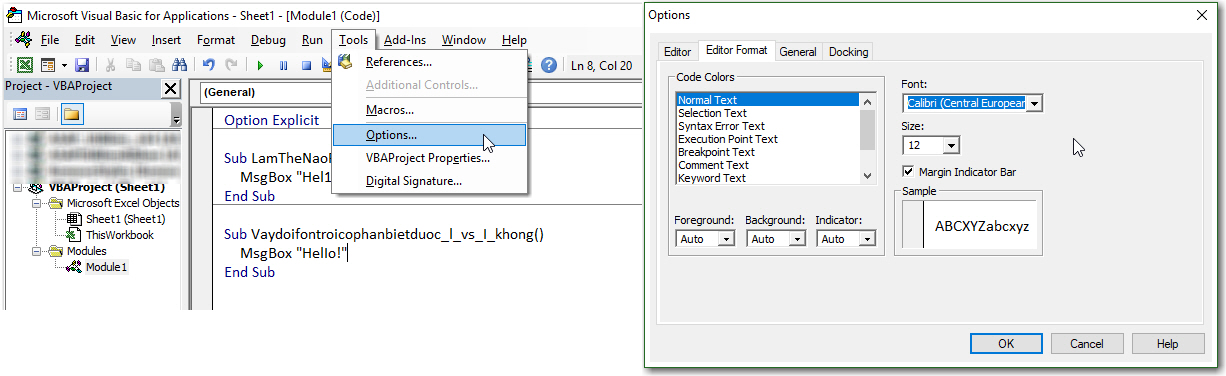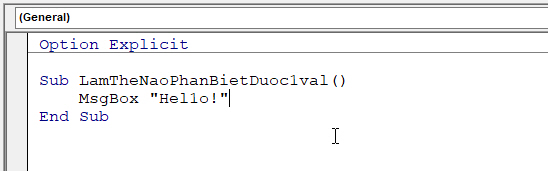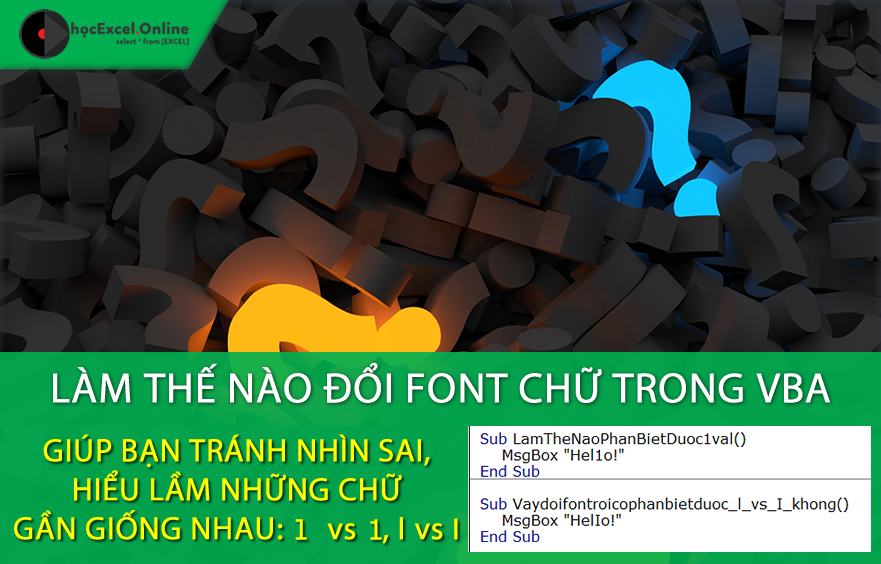
Thay Đổi Font Chữ Trong VBA Editor
VBA mặc định sử dụng font chữ Courier, đôi khi gây khó khăn trong việc phân biệt các ký tự giống nhau như số 1 và chữ l thường.
Thoạt nhìn, chúng trông rất giống nhau. Microsoft đã cung cấp tùy chọn thay đổi font chữ và màu sắc trong VBA editor để khắc phục vấn đề này và giúp bạn lựa chọn font chữ yêu thích.
Để thay đổi, bạn vào Tools -> Options -> Editor Format. Trong phần Normal Text, bạn có thể chọn font chữ mong muốn. Ví dụ, chúng ta chọn font Calibri.
Tuy nhiên, với Calibri, chữ l thường lại dễ nhầm lẫn với chữ I hoa. Mặc dù khi đứng gần nhau chúng ta có thể phân biệt được, nhưng nếu nằm trong một đoạn code dài, việc này cũng khá khó khăn.
Một lựa chọn khác là font Verdana. Với Verdana, việc phân biệt các ký tự trở nên dễ dàng hơn.
Việc thay đổi font chữ tưởng chừng như nhỏ nhưng sẽ giúp bạn làm việc với code VBA hiệu quả hơn, đặc biệt là khi phải xử lý những đoạn code dài và phức tạp.
Tóm lại, việc lựa chọn font chữ phù hợp trong VBA editor sẽ giúp bạn đọc và viết code dễ dàng hơn, tránh những nhầm lẫn không đáng có và nâng cao hiệu suất làm việc. Hãy thử nghiệm các font chữ khác nhau để tìm ra lựa chọn tốt nhất cho mình.